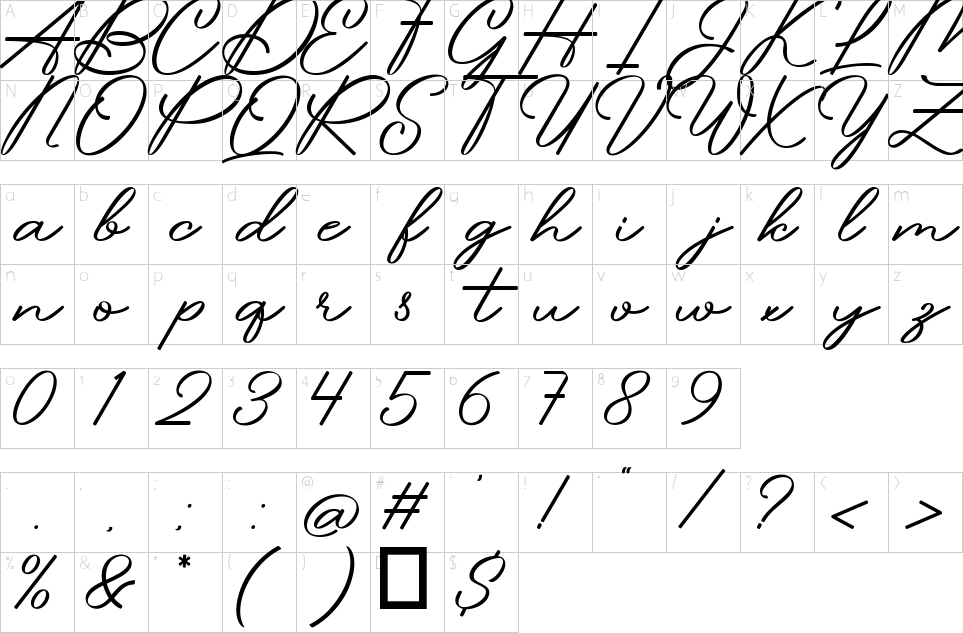
A Pitaloka Font é uma fonte grátis que oferece um visual atraente e natural, perfeita para quem busca gráficos agradáveis e versáteis. Desenvolvida pelo Naufal Labs, esta font pode ser facilmente utilizada tanto em sistemas Windows quanto Mac. Com seu design clean e elegante, a Pitaloka é uma escolha ótima para projetos gráficos diversos. A font foi descarregada mais de 1,314 vezes, o que evidencia seu valor como opção de fonte de confiança. Seja para o design de aplicativos, publicidade ou criação de materiais de marketing, a Pitaloka pode se destacar com sua simplicidade e qualidade. Descubra por si mesmo a versatilidade desta fonte e faça seu design se destacar.